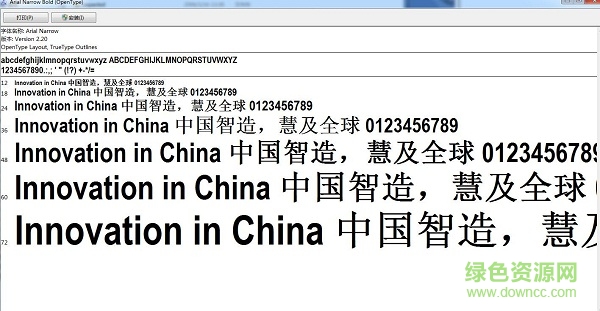
arial narrow 是什么字體?arialnarrow bold-gbpc-euc-h字體一款較粗的Arial無襯線字體,用在廣告、海報、平面設(shè)計等效果都很好,號召力強,需要的朋友快來下載吧!
Arial其實是Monotype Grotesque系列的變種。設(shè)計Arial時考慮到會在電腦上面使用,在字體及字距上都作了一些細微的調(diào)整和變動,以增加它在電腦屏幕上不同分辨率下的可讀性。
文字的主要功能是在視覺傳達中向大眾傳達作者的意圖和各種信息,要達到這一目的必須考慮文字的整體訴求效果,給人以清晰的視覺印象。因此,設(shè)計中的文字應避免繁雜零亂,使人易認,易懂,切忌為了設(shè)計而設(shè)計,忘記了文字設(shè)計的根本目的是為了更好,更有效的傳達作者的意圖,表達設(shè)計的主題和構(gòu)想意念。